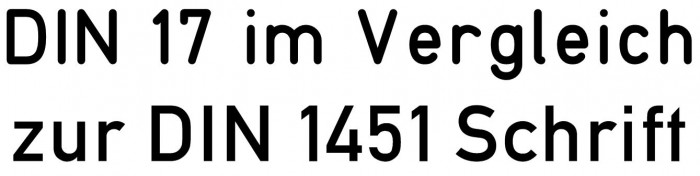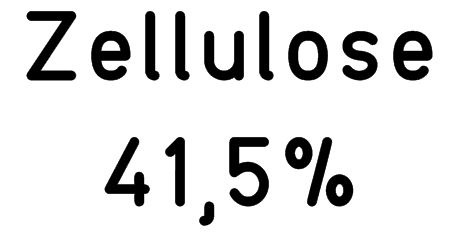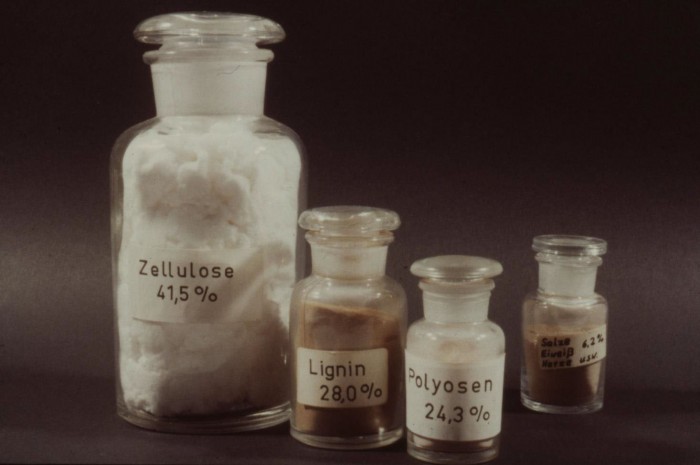
Welche Schriftart ist im Bild zu sehen? (Glasflaschen)
hat jemand eine Ahnung welche Schriftart ist es, auf den Dosen?
Und ich würde eher zu einer DIN 17 als der DIN 1451 greifen, denn solche Etiketen wurden damals mit einer Schriftschablone und Röhrchenfeder bzw Tusche-Füller beschriftet. Das ergibt bei gleichem Skelett der Buchstaben abgerundete Linienenden.
Am dichtesten am Original wird daher z.B. meine TGL 0-17 sein.
Und ich würde eher zu einer DIN 17 als der DIN 1451 greifen, denn solche Etiketen wurden damals mit einer Schriftschablone und Röhrchenfeder bzw Tusche-Füller beschriftet.
Hast du dir die Typ1451 angeschaut? Auch wenn der Name irreführend ist, ist sie nicht weiter von der gesuchten Schrift entfernt als die gängigen DIN-17-Vektorisierungen.
Die älteren (und noch nicht typografisch verfeinerten) DIN 1451 bzw TGL 0-1451-Schriften waren ja vom Skelet her völlig identisch mit der DIN 17, wobei der Unbterschied lediglich in dien Linienenden liegt. Die 1451 haben rechteckige Linienenden, die DIN 17 (und die 15° schräge DIN 16) dagegen vom Schreibgerät bedingt runde Linienenden.
Und was Lineto da gemacht hat, ist eben keine DIN 1451, sondern eine DIN 17.
[…] wobei der Unbterschied lediglich in dien Linienenden liegt.
Dieser Unterschied tritt gerade nicht bei der Typ1451 von Lineto auf, die ebenfalls mit runden Linienenden daherkommt.
In meinen Augen ist sie die schönere DIN 17; ich würde sie daher im konkreten Fall der DIN 1451 und TGL 0-17 vorziehen.